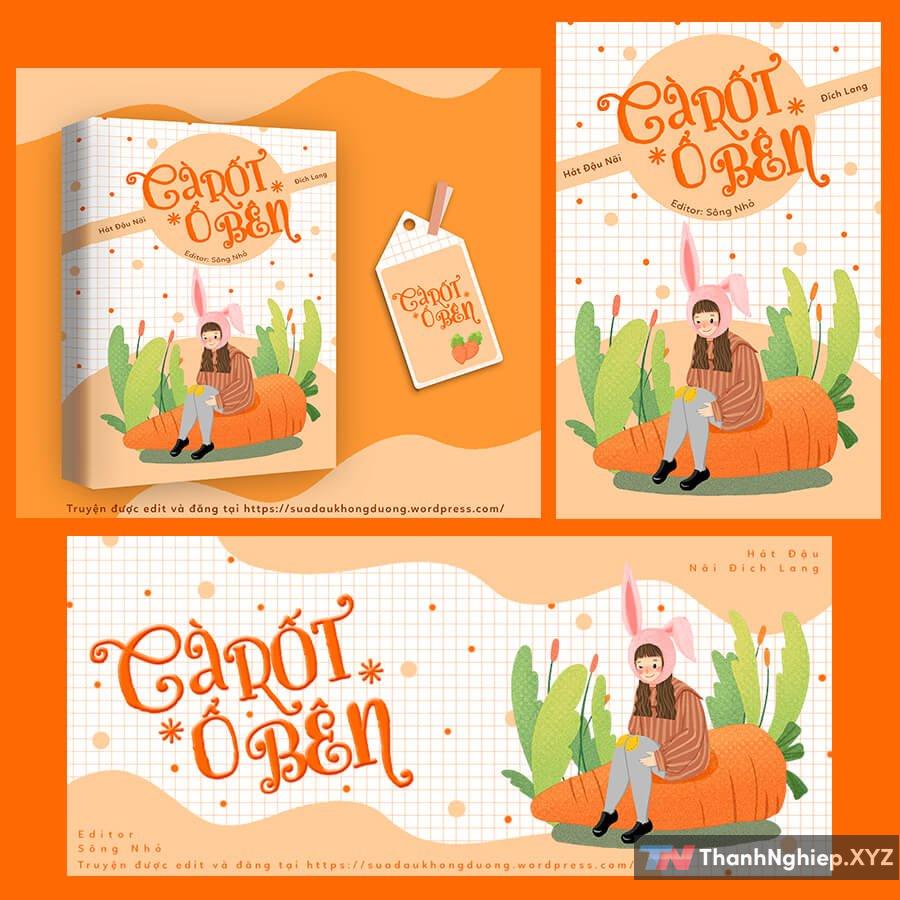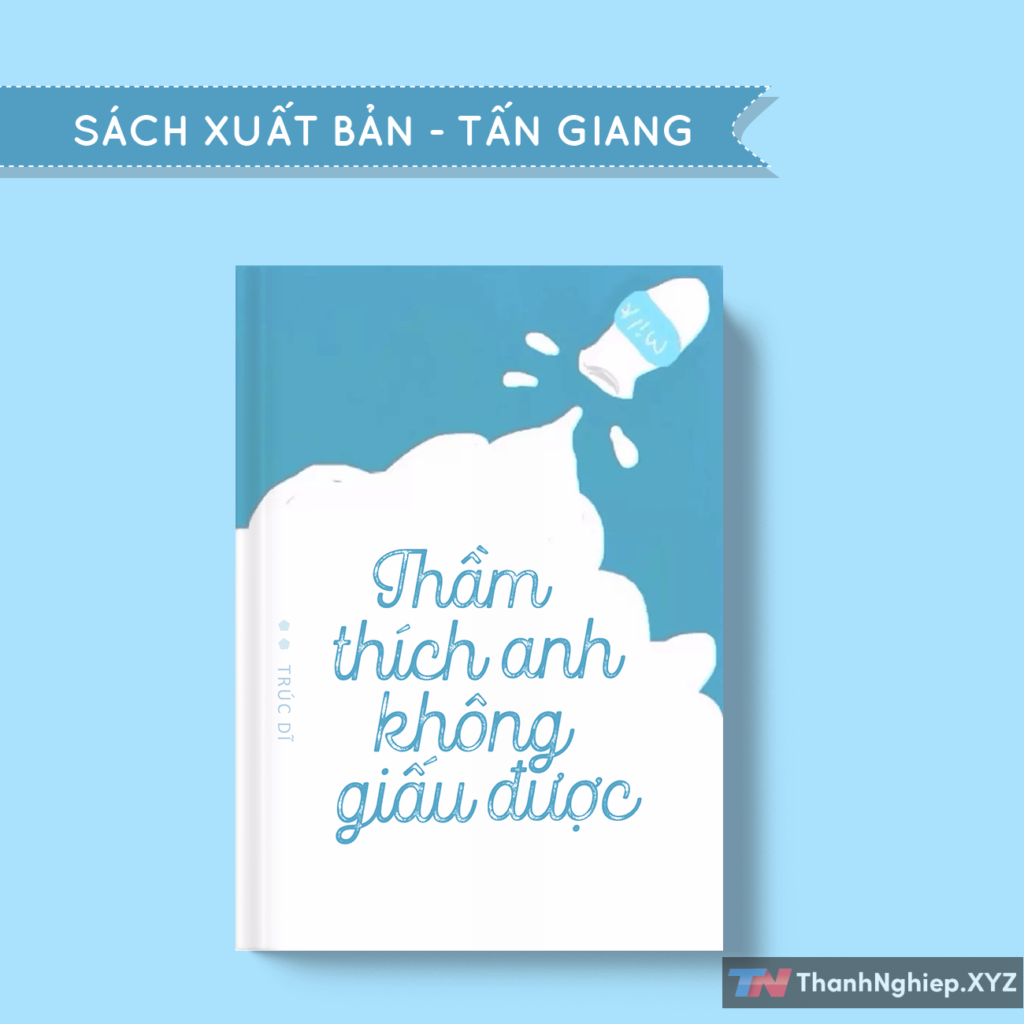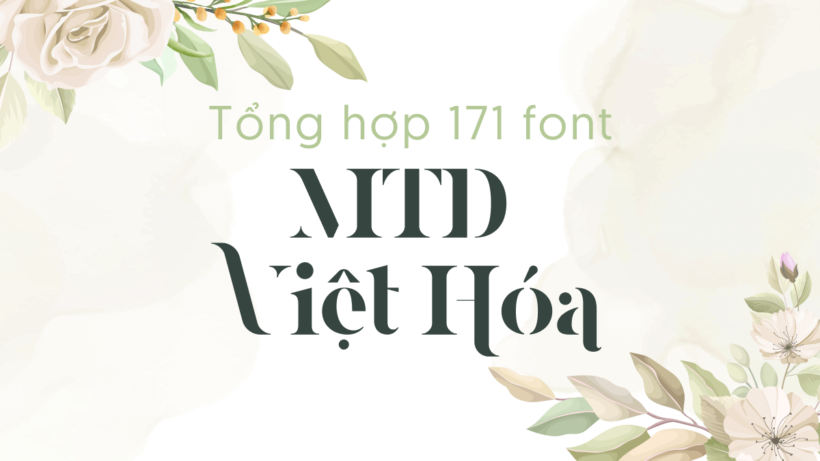
Đã bao giờ bạn bối rối trong việc tìm kiếm font việt hóa đẩm chất lượng mà lại hợp gu sáng tạo? Hãy cùng chào đón bộ 171 font MTD việt hóa – kho báu dành cho designer, content creator và bất kỳ ai yêu thích nghệ thuật chữ nghiệp.
Với sự đa dạng về phong cách và chất lượng đạt chuẩn cao nhất, bộ font này đảm bảo sẽ “ghi điểm” trong mắt bất kỳ khán giả nào.
Đặc điểm nổi bật của bộ font MTD việt hóa
Đầy đủ tính năng việt hóa:
Tất cả các font trong bộ sưu tập đã được việt hóa từng chi tiết, đảm bảo hiển thị đầy đủ các dấu sắc trong tiếng Việt, bao gồm đổi với các phong cách chữ ngoạn ngào như script, handwritten hay bold display.
Sự đa dạng về phong cách:
Bạn thích phông cách thanh lịch, tự nhiên hay ngộ nghĩnh, tinh nghịch? Bộ font này đầy đủ từ serif sang trọng đến sans-serif tối giản, cả handwriting “màu mắc” lẫn retro cá tính.
Dự án nào cũng được:
Tổng hợp hơn 171 font MTD việt hóa sẽ là bạn đồng hành cho mọi nhu cầu thiết kế: poster, banner, truyện tranh, in ấn hay thậm chí là thiết kế logo.
Chất lượng “thực sự”:
Wonderland Team đã kỳ công trong từng bước việt hóa, đảm bảo các font hoạt động mịnh mẽ, không lỗi và phù hợp với nhiều nền tảng.
Khác biệt là đẳng cấp:
Khác với các bộ font tràn lan trên mạng, bộ font MTD việt hóa đặc biệt ở chỗ: đường nét tinh tế, phong cách đồng bộ, và đem lại trải nghiệm đồng nhất cho dự án.
Ai sẽ yêu thích bộ font này?
- Họa sĩ truyện tranh: Tạo không gian sáng tạo tuyệt vời cho những lời thoại hay điểm nhấn.
- Marketer đang làm infographic: Biến thông tin khô khan thành tác phẩm nghệ thuật.
- Content creator: Muốn thêm gia vị cho những quote hay bài viết thu hút.
- Designer: Thiết kế banner, logo hoặc poster không thể thiếu font siêu độc lạ.
Tổng kết
Tổng hợp hơn 171 font MTD việt hóa chính là bí quyết cho một dự án thiết kế chất lượng cao đầy tính cá nhân. Dù bạn đang sáng tạo truyện tranh, bài PR hay infographic, bộ font này đảm bảo đáp ứng được mọi nhu cầu.
- HP DNS Gibsons
- HP Monstice
- MTD 1613 Basilius
- MTD Aaleyah Thick Stamp
- MTD Addictype
- MTD Adventures Unlimited
- MTD Afecta
- MTD Alex Calder
- MTD Alexandria
- MTD Almost Japanese
- MTD Amarone
- MTD Ampihan
- MTD Andrade Pro Script
- MTD Antique Spenserian
- MTD Architect
- MTD Ariestha
- MTD Attention Script
- MTD Auckland Script
- MTD Australian Script
- MTD Authemart
- MTD Auto Quick
- MTD Avelina
- MTD Babylonica ROB
- MTD Balerno
- MTD Balinice
- MTD Banthers
- MTD Beautiful Friends
- MTD Bechamel Roman
- MTD Bell Martellus
- MTD Bella Rose
- MTD Benton
- MTD Bhaltazar
- MTD Bibliophile Script
- MTD Bigilla
- MTD Black and Shadow
- MTD Black Night
- MTD Blue Island Std
- MTD Bon Ami
- MTD Brand Pro
- MTD Brignola PUA Script
- MTD Broadway
- MTD Brownstone Sans Hole
- MTD Brunette
- MTD Bubble
- MTD Buffied
- MTD Bunga
- MTD Capellina Script
- MTD Chalmers
- MTD Cheese Sauce
- MTD Christmas Miracle
- MTD Christmas Sound
- MTD Chuck Noon Script
- MTD City Stencil
- MTD Coffee Break Script
- MTD Creaky Frank
- MTD CS Delirian Script
- MTD CS Solange
- MTD Doppelganger Display
- MTD Douglass Pen
- MTD Ecstasy TTW
- MTD Elipses
- MTD Esther
- MTD Explorers
- MTD Fado
- MTD Fiftyes
- MTD Font Trang Trí
- MTD Fun Play Day
- MTD Gambit Nouveau
- MTD Genia
- MTD Geza Script
- MTD Gilroy
- MTD Girasol
- MTD Girly Things
- MTD Gogoia Deco
- MTD Good Day
- MTD Goodwater
- MTD Gorni
- MTD Great Vibes
- MTD Great Victorian Swashed
- MTD Greatlove
- MTD Greature
- MTD Habibe
- MTD Hatthira
- MTD Hello Paris
- MTD Hey August
- MTD Hillstown
- MTD Hipster
- MTD Hummingbird
- MTD JRS
- MTD Kaneiwa Alp
- MTD Karolin
- MTD Katherine Script
- MTD Konfuciuz
- MTD Kosova
- MTD Lastone
- MTD Letra Pro Headline
- MTD Levitee
- MTD Love
- MTD Lucy Rose
- MTD Lyrics Movement
- MTD Mavera
- MTD Megrim
- MTD MelamarCalligraphy
- MTD Middle Saxony Text
- MTD Midnight Tales
- MTD Milkstore
- MTD Mind Blowing
- MTD MK Broken Types
- MTD Monopola Script
- MTD MusashiBB
- MTD New Year_s Story
- MTD Oceania
- MTD Okashi
- MTD Old Finlander
- MTD P22 Kilkenny Swash Eureka
- MTD P22 Ruthie
- MTD Parnas
- MTD PC Snowballs
- MTD PF DaVinci Script Pro
- MTD PN Macabre Millionaire
- MTD Prida
- MTD QuangNinh_Thuphap
- MTD Quaver
- MTD Quimbly
- MTD Ranthing
- MTD Renaissance Garden
- MTD Romance Fatal Serif Pro
- MTD Rose Petals Two
- MTD Rosemary Signature
- MTD Rossegenia
- MTD Roughish
- MTD Royal Touch
- MTD Santiago
- MTD Santos Dumont
- MTD Scripture
- MTD Selva
- MTD Serenity
- MTD Shapely
- MTD Silver Crown
- MTD Sirunian
- MTD Skylar
- MTD Snow For Santa
- MTD Sofye
- MTD Spagheti Script
- MTD Spooksville
- MTD Spring Chicken
- MTD Stanwood
- MTD Starcity Script
- MTD Streetwear
- MTD Thank You So Much
- MTD The Beauty Blink
- MTD Thirsk
- MTD Tita Script
- MTD Traditian
- MTD Troyline Script
- MTD Twas The Night Before Christmas
- MTD Ultimus
- MTD Unicorn Calligraphy
- MTD UT Sugar Cane
- MTD Valky
- MTD Volloa
- MTD Voyage
- MTD VVD Golden Horn
- MTD Wanita
- MTD Whittier
- MTD William Letter Signature Script
- MTD Yerington
- MTD Yessy
- MTD Yolanda Princess
- MTD Youther Script
- MTD Yozakura JP